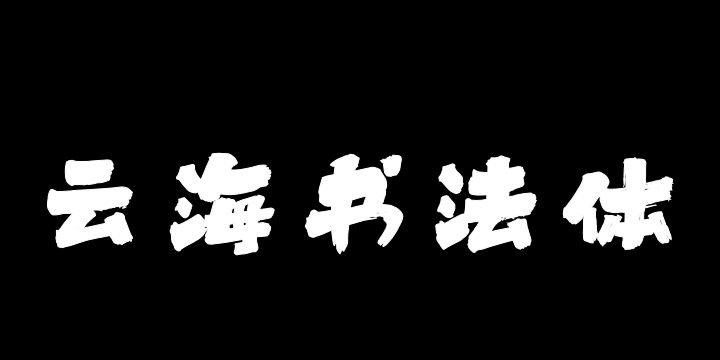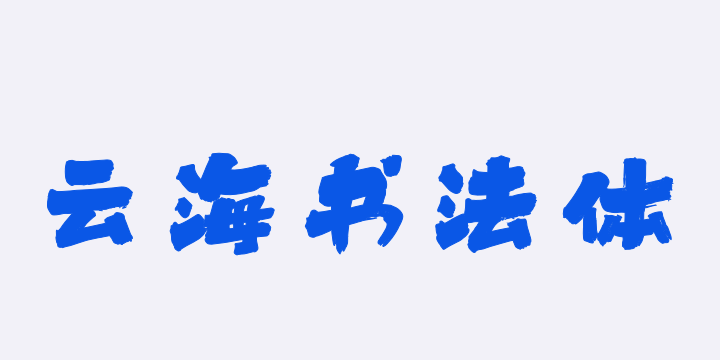
上首云海书法体 By 上首造字 商用字体
字体全名: 上首云海书法体
铸字厂: 上首造字
设计师: 胡博剑
字体简介: 上首云海书法体,简体中文约6763字,字体在风格上结合了和风书法的特点,又融入了现代设计理念,如简单的几何构型、大小强烈对比的趣味性。字体书写时强调运笔的力量与节奏,平衡传统书法与现代创新设计。字体整体具有力量但又不趣味活泼,适用于搭配标志、广告标语、商业广告、海报字体等高端属性。